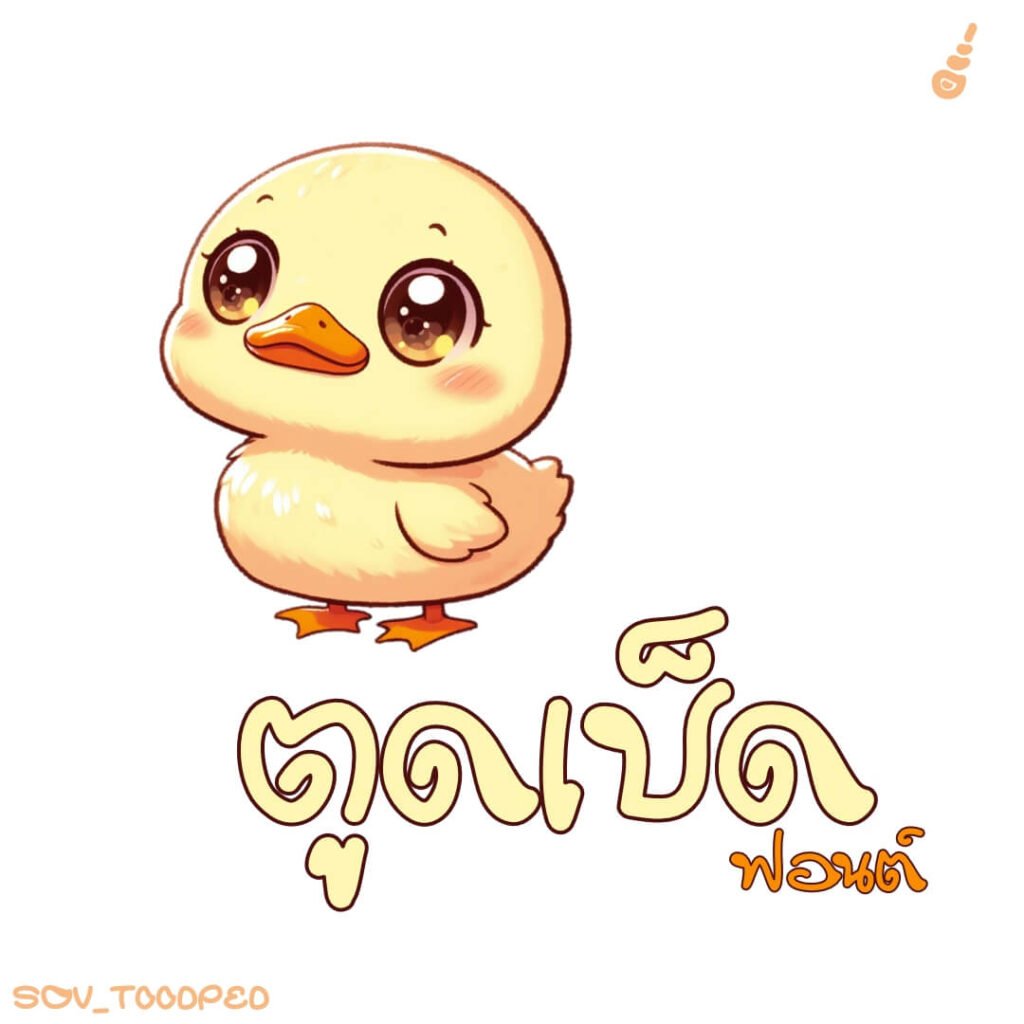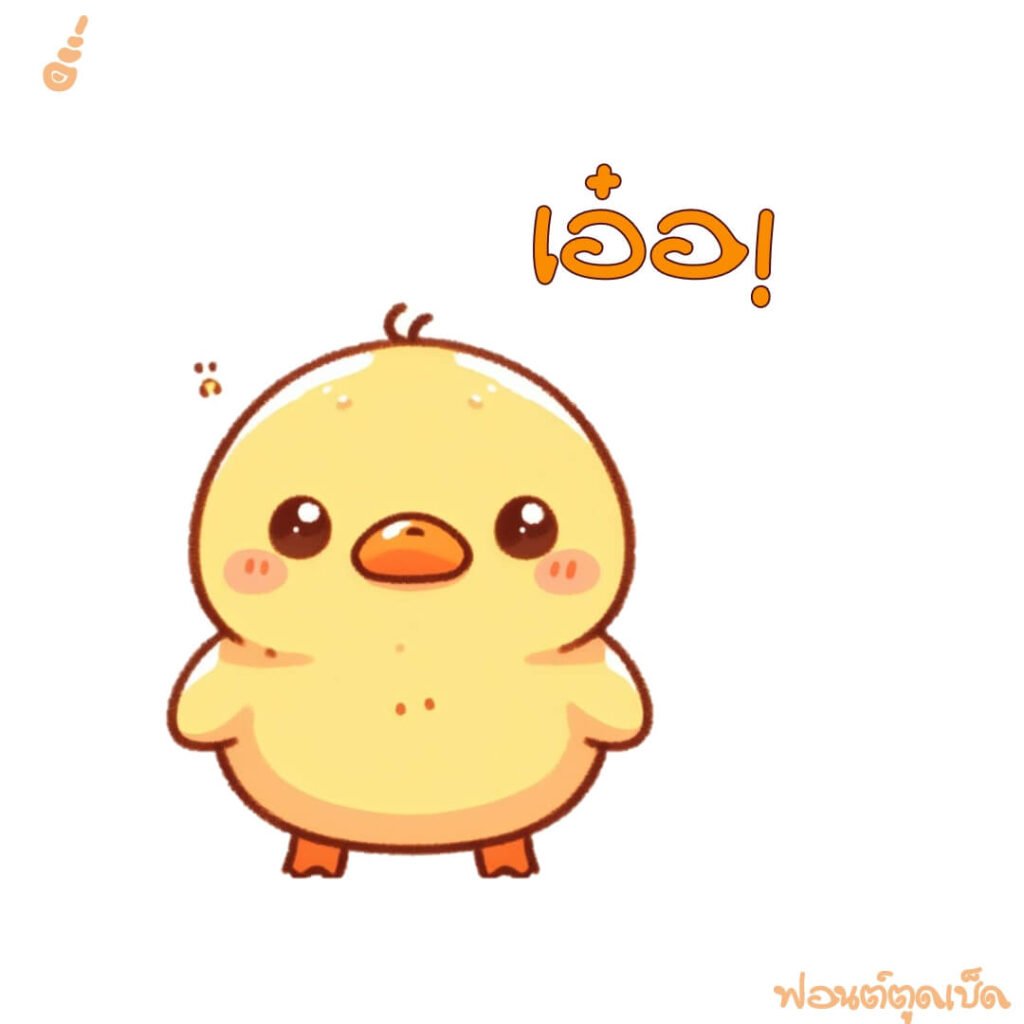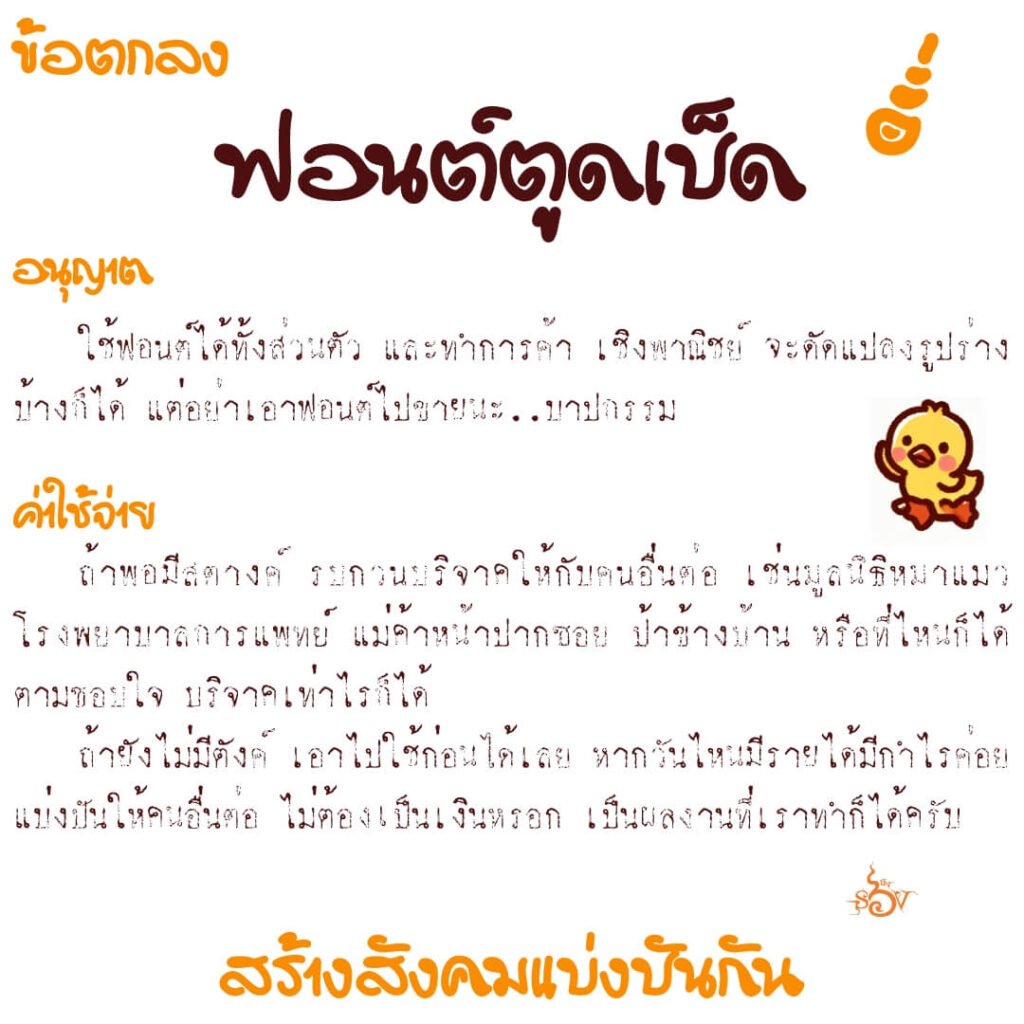
ตูดเป็ด (SOV_ToodPed)
อยากทำอักษรตวัดปลายหางให้งอนขึ้น เหมือนตูดเป็ด …ทำให้เกิดช่องไฟที่กว้างมากไป ต้องตามแก้ปัญหาให้วุ่นวาย
ตั้งใจให้เป็นฟอนต์พาดหัว แต่ดูเหมือนเป็นข้อความก็พอได้ …เชิญนำไปสะบัดตูดตามสบาย เงื่อนไขเขียนไว้ชัดเจน